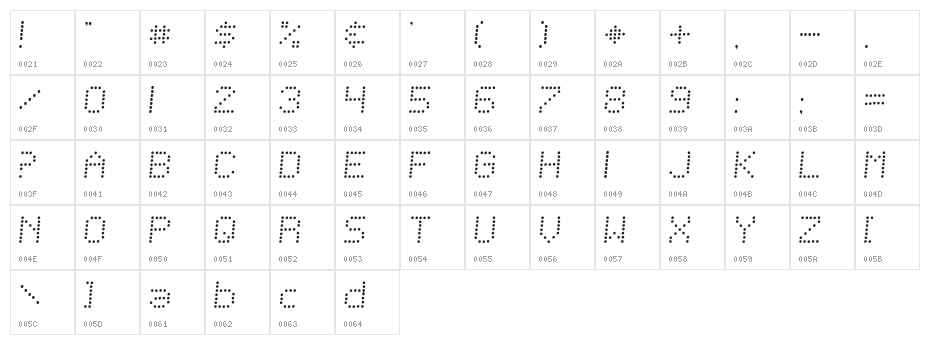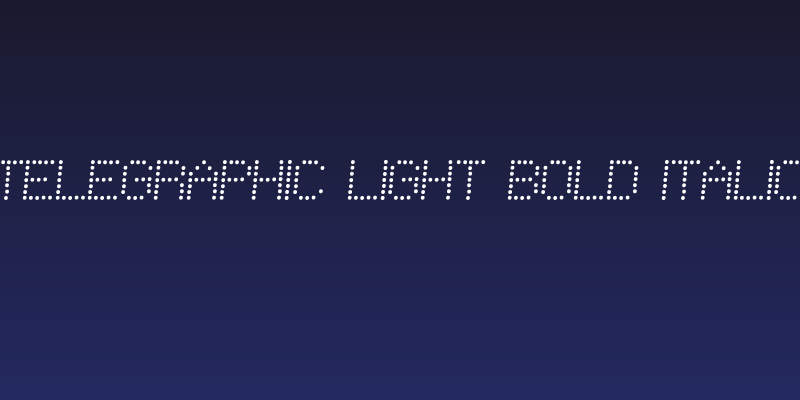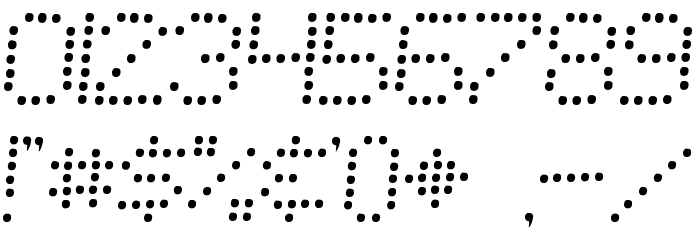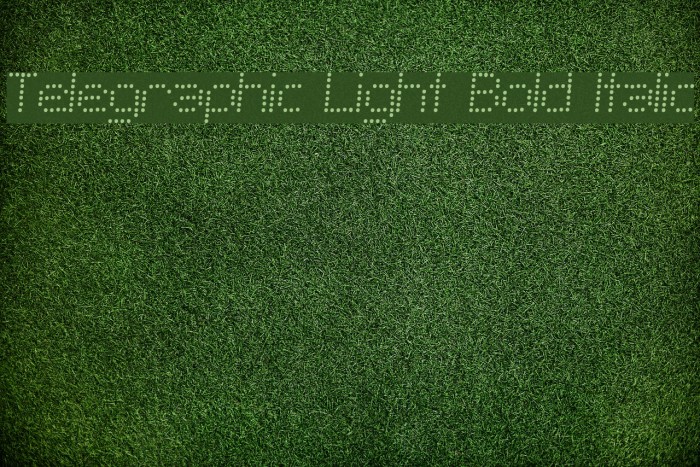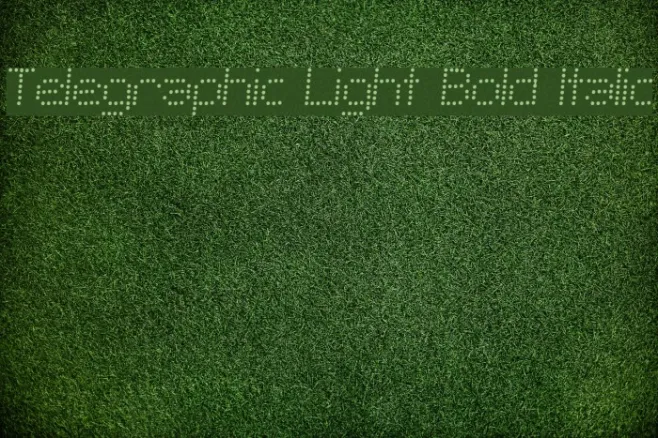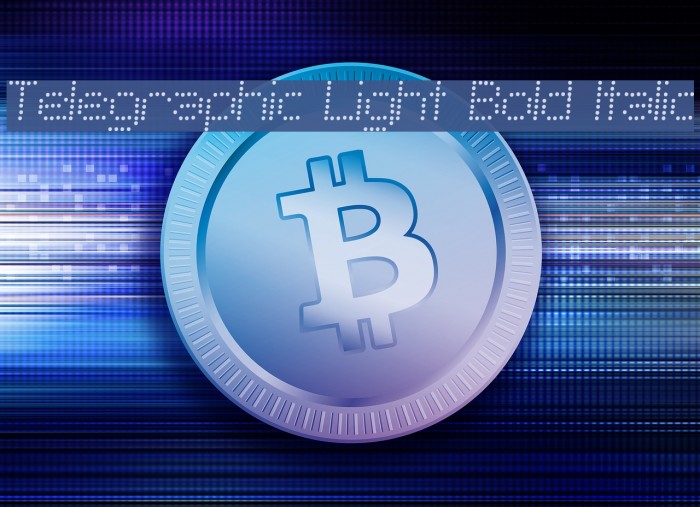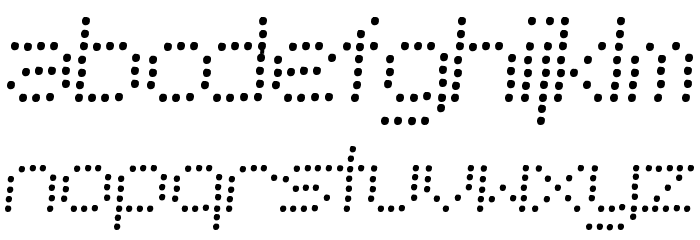
Telegraphic Light Bold Italic Font
✎ Dotted
| Projets proposés | Ideal for digital displays, tech-themed posters, futuristic branding, and retro-inspired designs. |